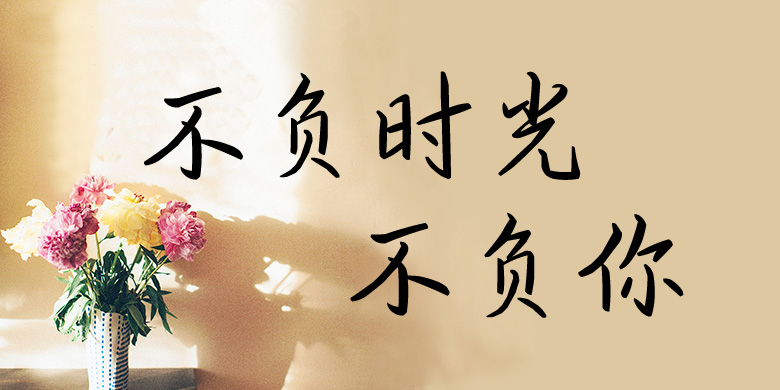
方正手迹-不负时光不负你
方正手迹-不负时光不负你,这款字体结构工整、笔画清晰,兼顾美观与易读性,适用于标题、正文、海报、包装、LOGO 等多种场景。字形优雅稳定,风格百搭耐看,适配日常排版与创意设计,让文字呈现更舒适、更具质感。方正手迹-不负时光不负你一笔一画,皆是细节,以均衡的比例、流畅的线条打造舒适视觉体验,字形端正大气,风格简约现代。无论是商业设计、品牌宣传还是日常排版,都能轻松驾驭,让文字更有格调与力量。方正手迹-不负时光不负你字体下载。
不负时光不负你是一款毛笔书写字体,字体书法气息浓厚,结构严谨,比例合理,整体风格典雅大方,自然美观。适用于文艺类的书刊、品牌广告和产品包装设计、影视综艺字幕,以及社交网络的个性化用字。